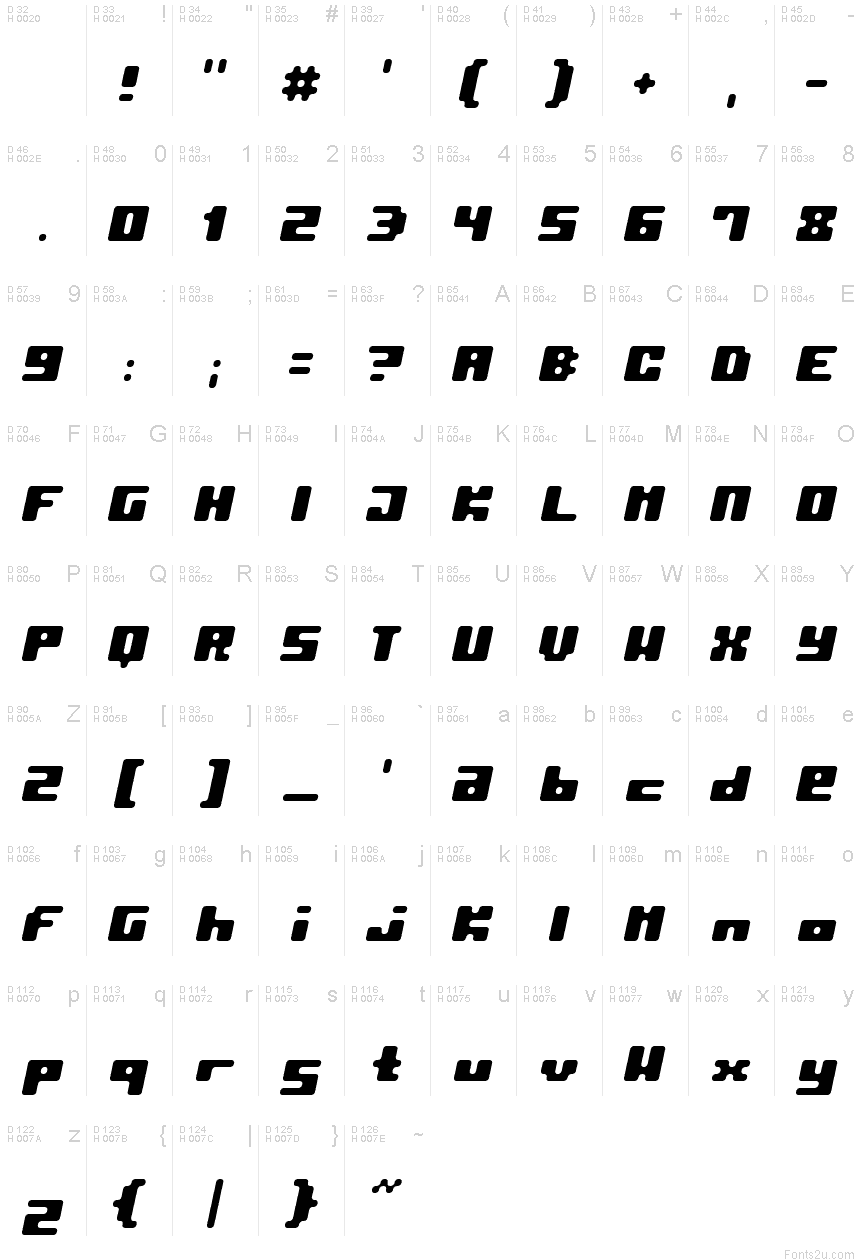
Pormask Remix od TarmSaft font factory to darmowy, futurystyczny krój pisma typu display o niskiej, formowanej sylwetce i masywnych, zaokrąglonych wycięciach, dzięki którym litery sprawiają wrażenie odlanych, a nie narysowanych. Szerokie, miękkie kształty i otwory w kształcie pigułek nadają jej klimat techno z końca lat 90., ale całość pozostaje zabawna, a nie chłodna.
Ten darmowy font idealnie pasuje do ulotek klubowych, logotypów gier, okładek płyt, nagłówków plakatów i plansz tytułowych, wszędzie tam, gdzie krótki tekst potrzebuje skompresowanego, maszynowego „odbicia”. Sprawdza się również w napisach na opakowaniach czy banerach internetowych, ponieważ litery łączą się w gładki, niemal płynny rytm, dzięki czemu nawet proste słowa zyskują graficzny charakter.
Pormask Remix